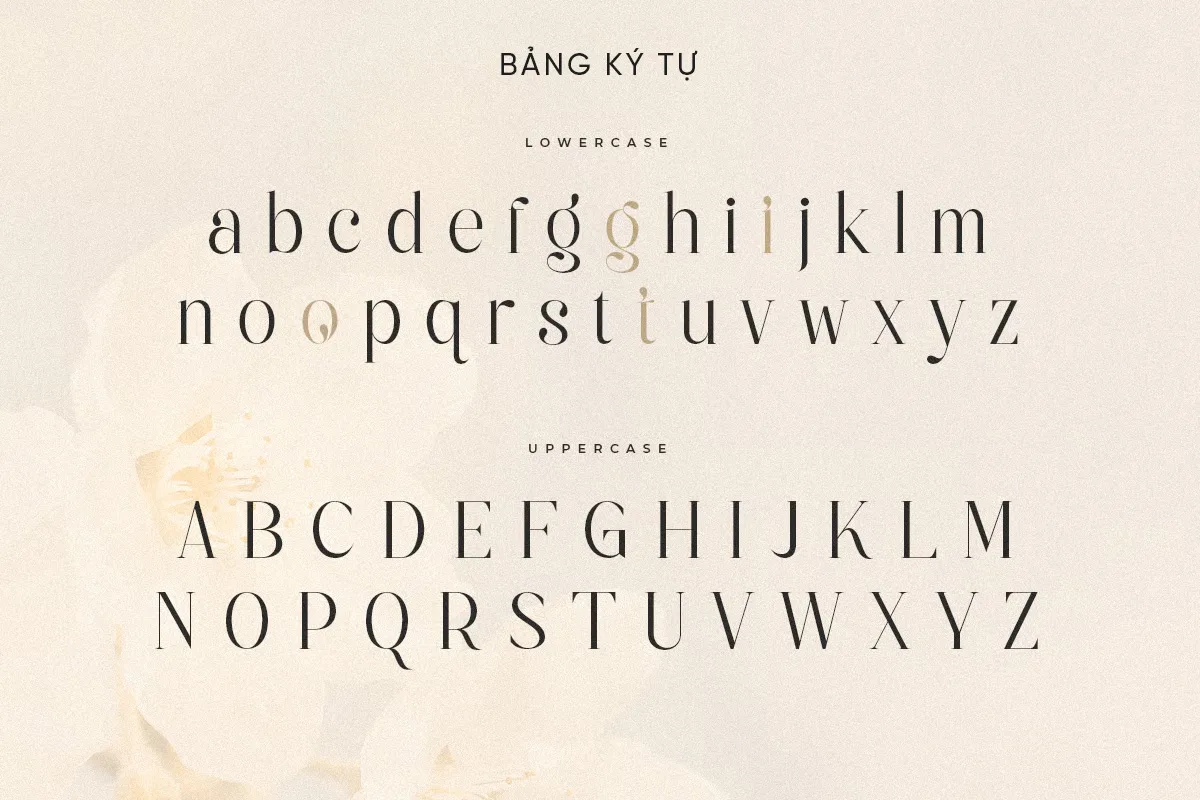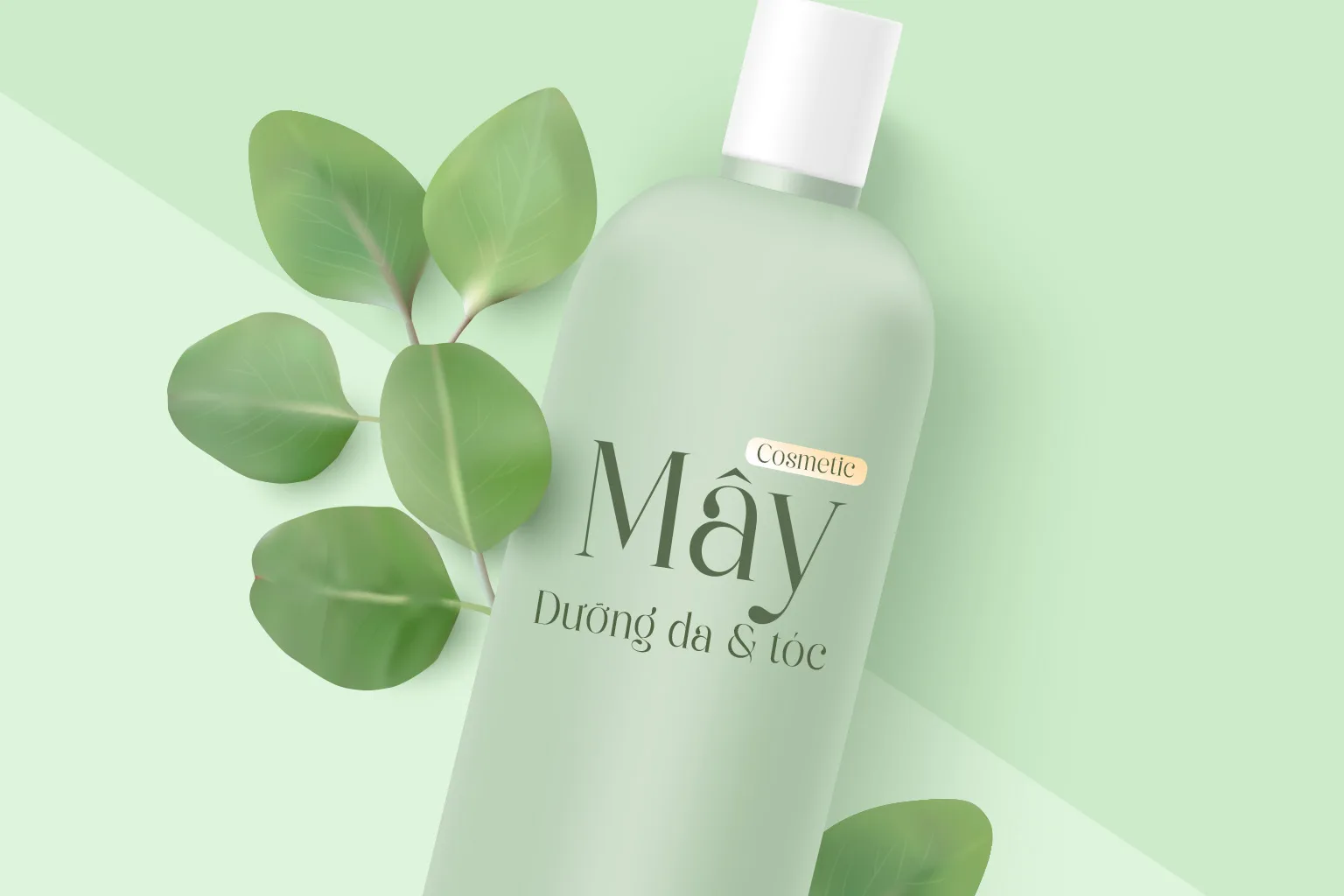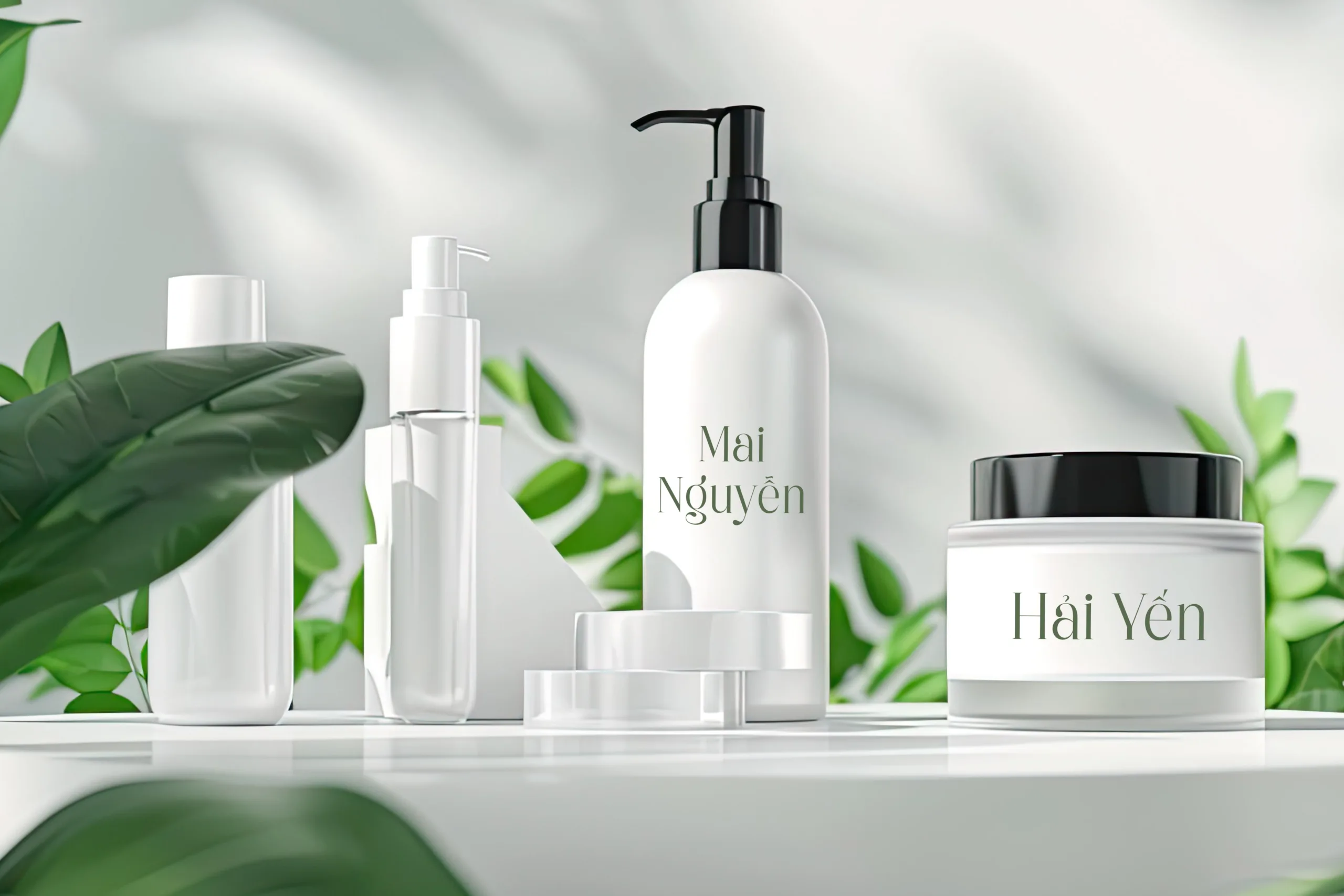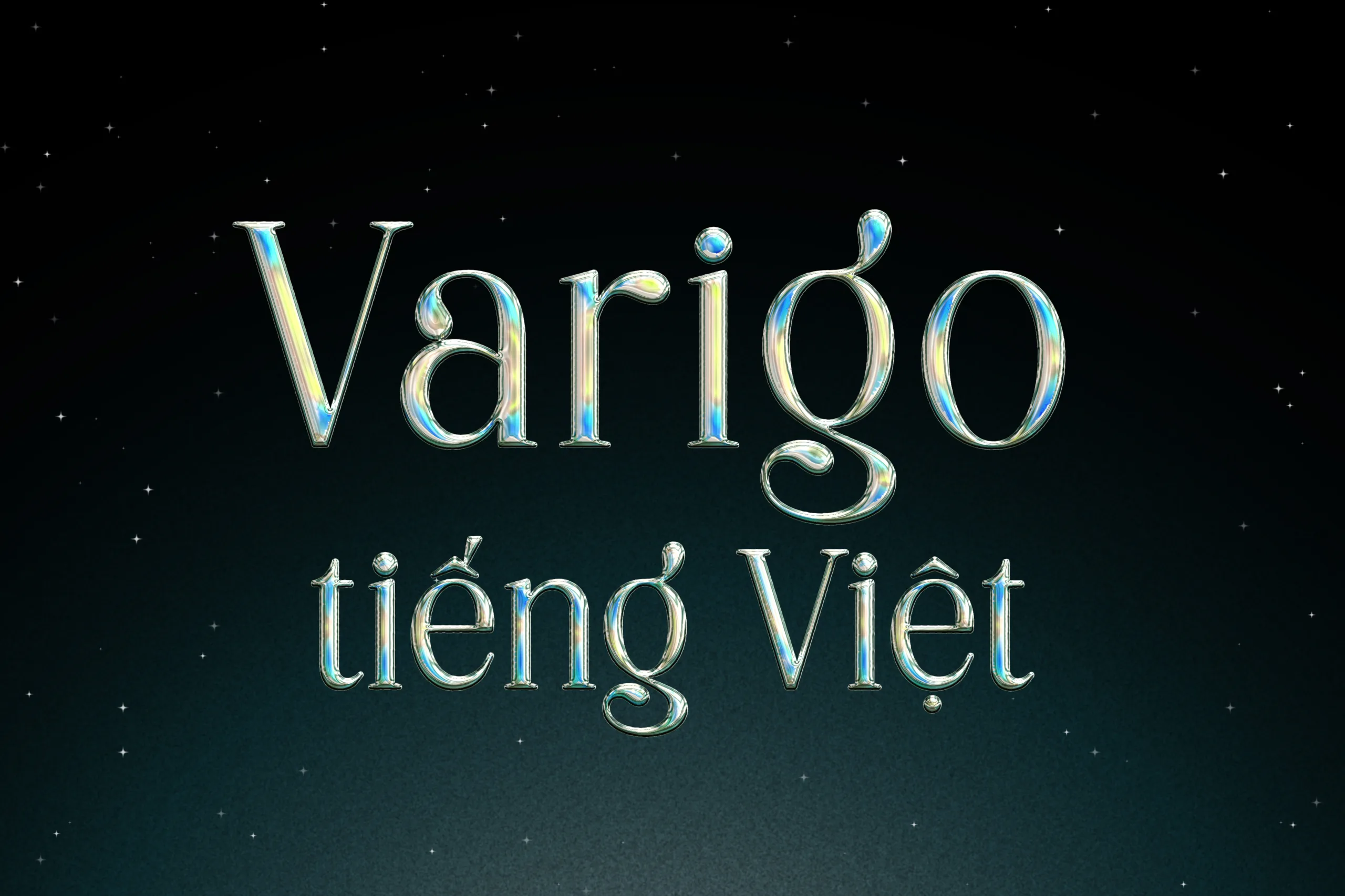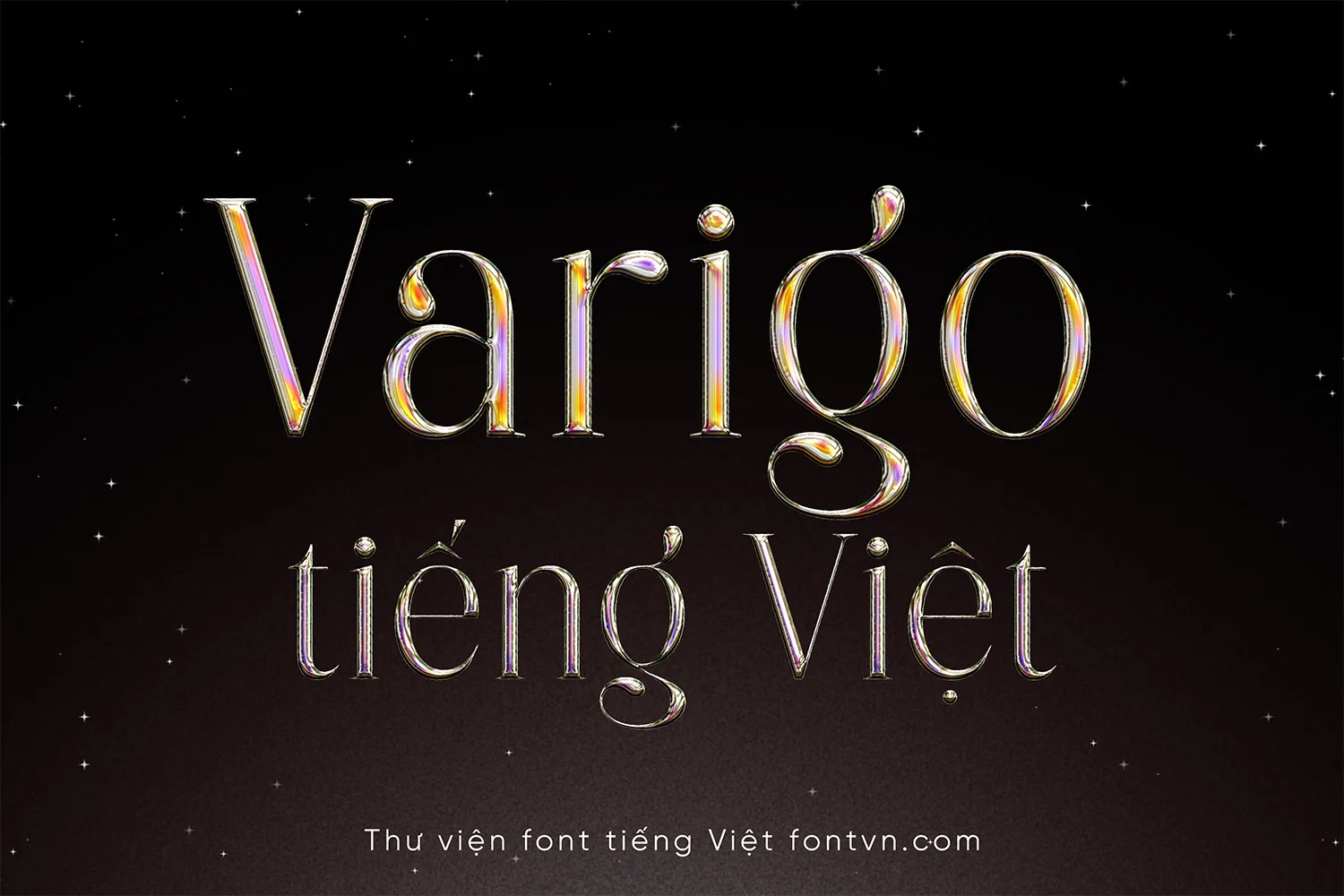
DVN Varigo tiếng Việt – Premium Serif Font Cho Logo & Thương Hiệu
DVN – Varigo là font serif mang phong cách hiện đại, kết hợp giữa những đường nét thanh mảnh và độ tương phản cao, tạo nên vẻ đẹp sang trọng, tinh tế và đầy cuốn hút. Bộ font được thiết kế để phù hợp với các dự án cần sự cao cấp, thời trang và chuyên nghiệp, đồng thời vẫn đảm bảo khả năng đọc tốt ở cả tiêu đề lẫn nội dung ngắn.
Với các đường cong mềm mại, chân chữ sắc nét và tỷ lệ ký tự cân đối, DVN – Varigo mang đến cảm giác thanh lịch đặc trưng của phong cách Luxury Editorial. Font đặc biệt phù hợp cho những thiết kế yêu cầu tính thẩm mỹ cao và nhận diện thương hiệu nổi bật.